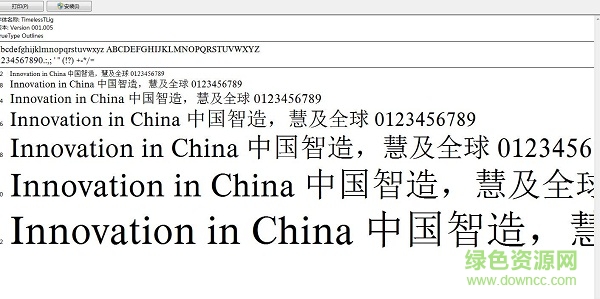
timelesstlig
timelesstlig字體是一款適合排正文及廣告設(shè)計(jì)的襯線字體,字體的機(jī)構(gòu)嚴(yán)謹(jǐn)端正,線條粗細(xì)勻稱,十分符合字體構(gòu)形規(guī)律,表現(xiàn)力強(qiáng),小伙伴們快來本站免費(fèi)下載吧!
timelesstlig字體